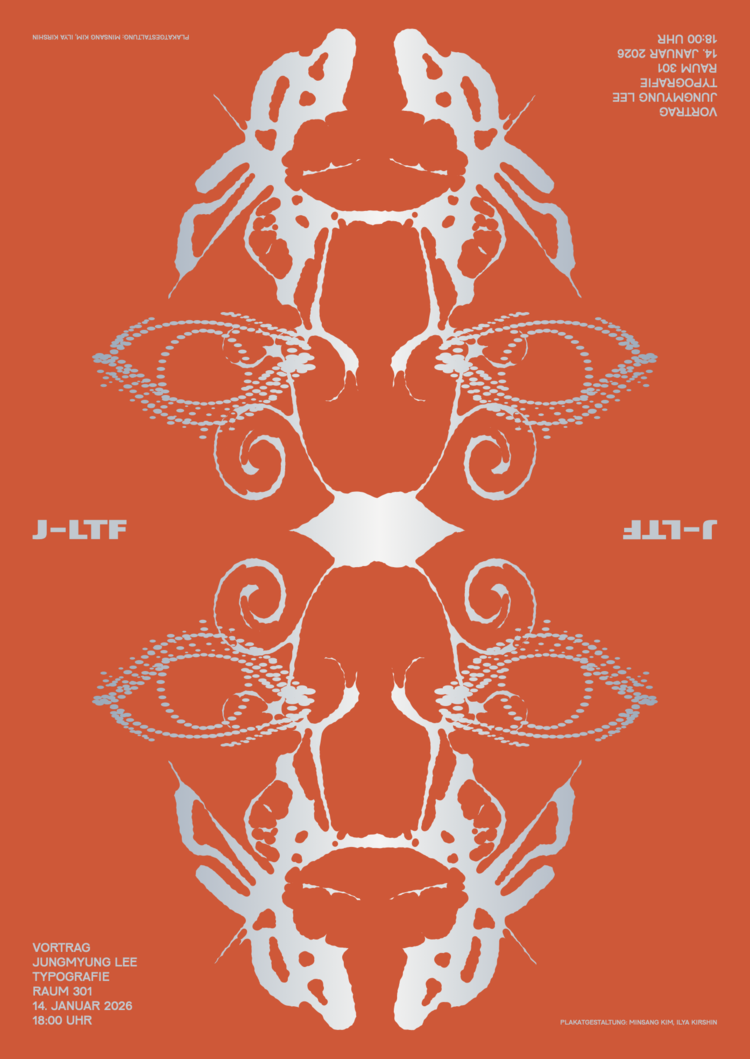
Jungmyung Lee: Typefaces have other interests besides words.
Jungmyung Lee ist Grafik- und Schriftdesignerin und lebt in Amsterdam, wo sie die unabhängige Typefoundry J-LTF (Jung-Lee Type Foundry) betreibt. Mit J-LTF konzentriert sie sich in erster Linie darauf, Geschichten zu erzählen und Schriftarten als fiktive Charaktere und deren Emotionen zu erforschen. Schriftarten durchleben einen eigenen Lebenslauf, und Jungmyung Lee lässt sie dieses imaginäre Leben in verschiedenen Medien erkunden: Ihre Schriftarten führen Gespräche an Ausstellungswänden, dienen als Untertitel in Musikvideos, die als Specimen entstanden sind, oder werden von Künstler_innen und Schriftsteller_innen in der experimentellen Publikationsreihe Real-Time-Realist verwendet, die mit Hilfe von Texten ein Spektrum von Emotionen erforscht. Die zweite und aktuelle Ausgabe von Real-Time-Realist, die unter J-LTF PRESS veröffentlicht wurde, beschäftigt sich mit Ekstase, Freude, Gelassenheit und Liebe. Uns interessiert im Rahmen des Seminars auch ihr Umgang mit Revivals, beispielsweise Limpet, und ihre Zusammenarbeit mit Karel Martens.